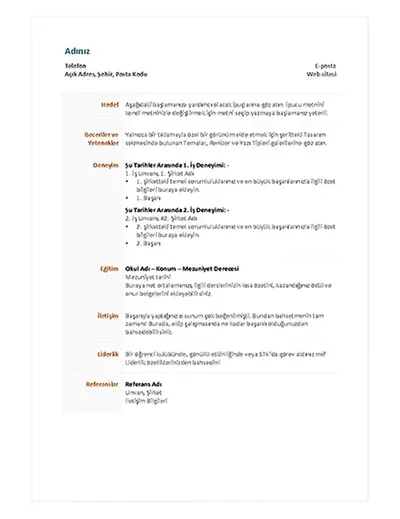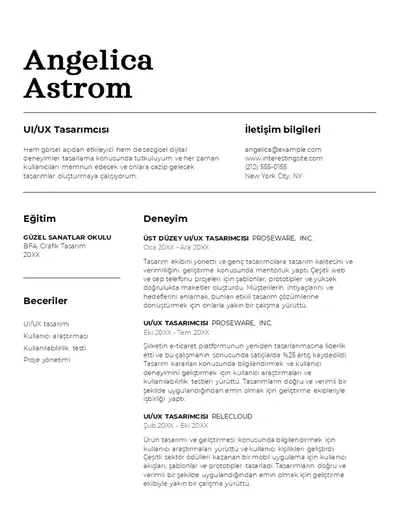
Doğru özgeçmiş yazı tipini seçmek, güçlü bir ilk izlenim bırakmanın en etkili yollarından biridir. Yazı tipleri güvenilirliği ve kişiliği yansıtabilir, profesyonelliği destekleyebilir ve ayrıntılara dikkat edilecek şekilde özgeçmişi parlatabilir.
Herhangi bir iş başvurusu için en iyi altı özgeçmiş yazı tipi
En iyi özgeçmiş yazı tipi, sayfada iyi görünmekle kalmaz. Yazı tipi seçimi, özgeçmişin nasıl okunduğunu, derecelendirildiğini ve hatırlandığını şekillendirir. İşte özgeçmiş taslağı hazırlamak için mükemmel olan en iyi profesyonel görünümlü yazı tipleri, tümü Microsoft WordWord'de mevcuttur.
1. Calibri yazı tipi
Modern bir sans serif yazı tipi olan Calibri, kurumsal altın standart haline gelmiştir. Okuması basit olan Calibri, profesyonellik ve otorite yayıyor. Kalın ve açık stillere sahip bu sans serif yazı tipi, her türlü ölçüye uyacak şekilde kolayca uyarlanabilir. Hukuk, finans ve sağlık gibi kariyerler için mükemmel bir uyum sağlayan Calibri, temiz ve profesyonel bir görünümün öncelikli olduğu her role uygundur.
2. Garamond yazı tipi
Klasik bir serif yazı tipi olan Garamond, profesyonel yayıncılıkta ve resmi belgelerde güvenilir bir seçimdir. Yazı tipinin küçük boyutlarda kolayca okunabilmesi, özgeçmişe otoriter ve zarif bir görünüm kazandırır. Garamond, geleneksel, yüksek güvenilirlikli bir sunuma değer verilen akademi, yayıncılık, hukuk ve yönetici pozisyonlarındaki roller için güçlü bir seçimdir.
3. Montserrat yazı tipi
Montserrat, özgeçmişe temiz ve ulaşılabilir bir görünüm kazandırır. Basılı reklamlar ve kentsel sokak tabelaları için tercih edilen bir yazı tipi olan Montserrat, yaratıcı alanlar, sağlık ve emlak alanlarındaki özgeçmişler için doğal bir seçimdir. Bu sans serif yazı tipi, son derece net ve taranabilir olmakla birlikte cesur bir görünüme sahiptir.
4. Candara yazı tipi
Candara, aşırı resmi olmadan gösterişli görünen zarif ve şık bir seçenektir. Kendine özgü tarzıyla kolayca okunabilen bu yazı tipi, daha az metin içeren özgeçmişler için uygundur. birleştirilmiş özgeçmiş biçimindedir ve özellikle staj, yazılım ve BT rolleri için iyi çalışır.
5. Cambria yazı tipi
Cambria, güvenilirliği ve profesyonelliği yansıtan geleneksel, dengeli bir serif yazı tipidir. Şunun için tasarlandı: Küçük metin boyutlarında ekranda kolay okuma olan (opens in a new tab) Cambria, her özgeçmişe uyan gelişmiş bir seçenektir. Bu serif yazı tipi yönetim, insan kaynakları ve liderlik rolleri için uygundur ve tasarımı matematik ve fen sembollerini desteklediğinden mühendislik ve mimarlık özgeçmişleri için hoş bir seçenektir.
6. Aptos yazı tipi
Aptos, Microsoft WordWord ve Microsoft 365'te varsayılan yazı tipidir ve net, taranabilir bir özgeçmiş oluşturmak için çağdaş stili güçlü okunabilirlikle dengeler. Daha sıcak, daha nötr bir tonla modern ekranlarda okunabilirlik için tasarlanmış, Aptos (opens in a new tab) , başlıklar ve gövde metni arasında uyum sağlayan esnek bir sans serif yazı tipidir. Bu çağdaş yazı tipi teknoloji, sağlık ve yönetim uygulamaları için çok uygundur.
7. Arial yazı tipi
Arial, özgeçmişe profesyonel ve kolay taranabilir bir görünüm kazandıran temiz, anlaşılır bir sans serif yazı tipidir. Esnekliği onu ister dijital ister basılı olarak paylaşılsın, farklı iş rolleri ve kariyer aşamalarındaki özgeçmişler için pratik bir seçim haline getirir. Bu düzgün ve tutarlı yazı tipi, özellikle kurumsal, müşteriye yönelik ve iş odaklı uygulamalarla uyumludur.
Profesyonel bir özgeçmiş yazı tipi nasıl seçilir
Uygun yazı tiplerinin kısa bir listesi seçildiğinde, bir sonraki adım doğru eşleşmeyi bulmaktır. iş başvurusu. İş rolüne ve kıdem düzeyine göre doğru yazı tipini seçmek, her iş sektörünün kültürel ve profesyonel nüanslarının yanı sıra potansiyel işverenler üzerinde bırakması gereken izlenimi anlamayı içerir. İşte en iyi yazı tipini bulmanıza yardımcı olacak bazı yönergeler.
İş rolünü ve seviyesini göz önünde bulundurun
Farklı iş rolleri ve kıdem düzeyleri bir özgeçmiş tasarımının ve yazı tipinin ne kadar yaratıcı ve resmi olması gerektiğini etkileyebilir. Rolün kıdem düzeyini (giriş seviyesi, orta seviye veya kıdemli) göz önünde bulundurun; çünkü bu, yazı tipi seçiminin ne kadar yaratıcı özgürlük gerektirebileceğini belirler.
Örneğin: Calibri, özgeçmişe yönetim rolü için temiz ve profesyonel bir görünüm kazandırabilirken, Montserrat, yaratıcı alanlardaki roller için daha çağdaş bir his katabilir.
Çalışma alanını düşünün
Her mesleğin ve çalışma alanının kendine özgü değerleri ve beklentileri vardır. Hukuk, tıp, devlet ve finans gibi resmi çalışma alanları için oluşturulan özgeçmişler güvenilirliği ve profesyonelliği yansıtmalıdır, bu nedenle Aptos ve Calibri gibi yazı tipleri doğal olarak uygundur.
- TWordWord'de özgeçmiş yazı tipi ve yazı tipi boyutu nasıl düzenlenir?
Word'te özgeçmiş açın, güncelleştirilecek metni seçin ve yeni bir yazı tipi seçmek için giriş sekmesindeki yazı tipi açılan listesini kullanın. Yanındaki yazı tipi boyutu alanını kullanarak metin boyutunu ayarlayın. Tüm başlıkları veya gövde metnini tek seferde güncelleştirmek için stiller galerisinde ilgili stile sağ tıklayın ve değiştir'i seçin. Değişiklik belgenin tamamında otomatik olarak uygulanır. Word'da belgeleri düzenlemenin ve biçimlendirmenin daha fazla yolu için Belge Düzenleyicisi'ni seçin.